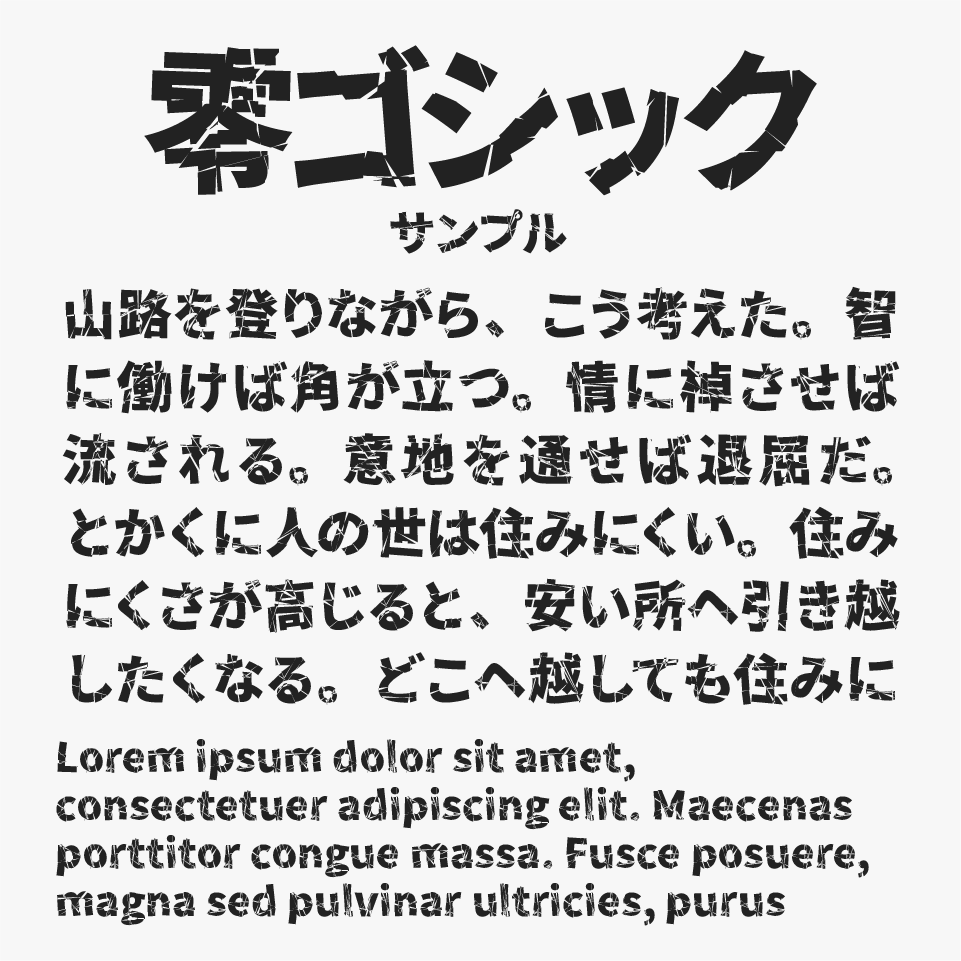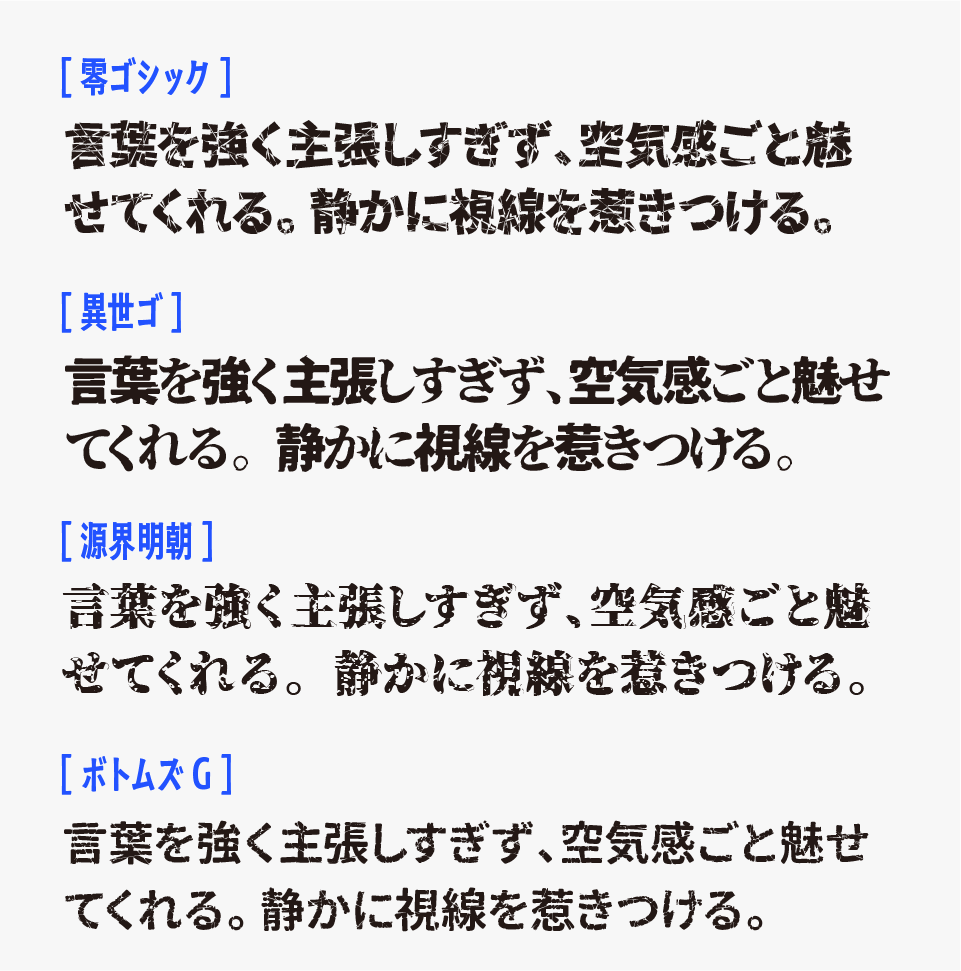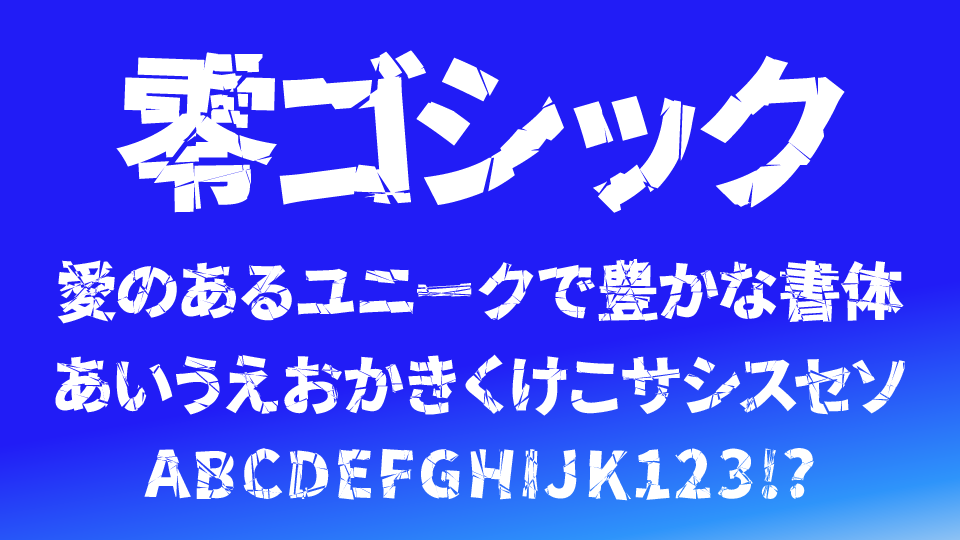
零ゴシックフォントは、「源ノ角ゴシック」をベースに、文字に“割れ”や“欠け”の質感加工が施された、インパクト抜群のデザイン系ゴシック体フォントです。
まるでガラスにヒビが入ったような鋭い亀裂表現が特徴で、かっこよさと荒々しい空気感をあわせ持っているフォントです。普通のゴシック体では出せない緊張感や破壊的な雰囲気があり、タイトルやロゴに使うだけでも一気に存在感を演出できるフォントです。
こうした割れ加工は、通常だと文字加工ソフトなどで手作業することも多いですが、零ゴシックは最初からデザインに組み込まれているため、文字を打ち込むだけでインパクトのあるビジュアルを作れるところも魅力です。
サムネイル・ゲーム・MV・サブカル・ダーク系デザインなどとも相性が良く、クールでユニークなタイトル表現をしたい場面にもぴったりなフォントとなっています。
零ゴシックフォントは、加工デザインが見えるように、タイトルやキャッチコピーなどで使うと効果的ですが、比較的に小さいサイズになっていても、文字に入っているヒビが入っている雰囲気はきちんと感じることができます。
ほかの質感系デザインフォントと比較してみると、零ゴシックは、ヒビや亀裂の加工表現が特に印象的で、独特な味わいがあります。比較フォントは、異世ゴ、源界明朝、ボトムズGと比較しています。どのフォントも質感がユニークなので、ぜひあわせてチェックしてみてください。
収録文字は、オープンフォント「源ノ角ゴシック」がベースになっているので、ひらがな・カタカナ・漢字など8000字以上揃って収録されています。